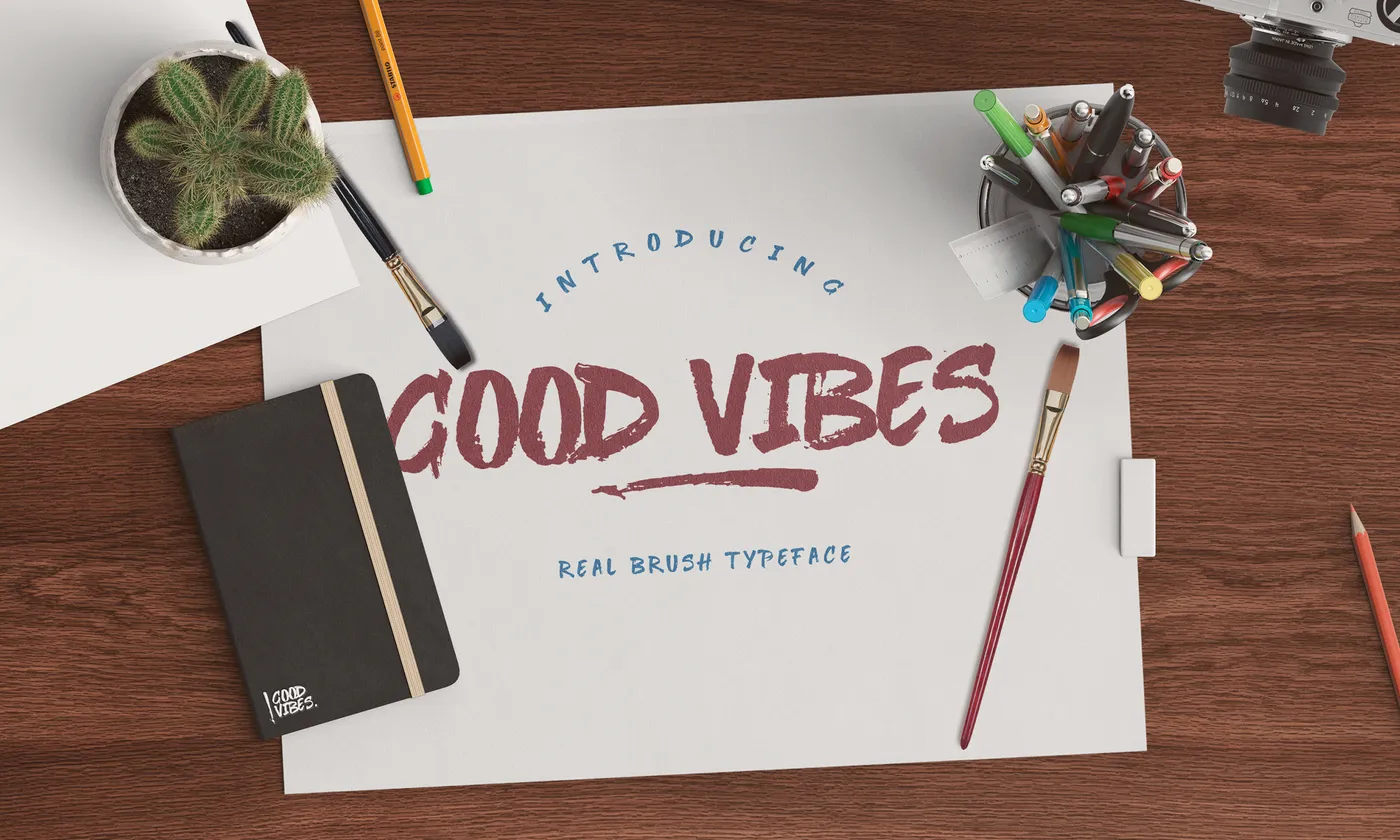
Good Vibes Brush Font – Download Grátis
Descubra a beleza contida na Good Vibes Brush Font, uma fonte script criada com amor pelo designer Hamilton. Esta fonte é perfeita para aqueles que buscam um estilo de brush que se destaca em seus projetos digitais. Ela oferece um toque especial e encantador, especialmente adequado para aplicativos como logos, anúncios, cartões postais e criações gráficas no geral. Good Vibes é mais do que simplesmente uma fonte: ela é um sentimento, uma energia positiva que se transfere de cada traço à outra. Cada letra foi criada a partir da forma como seu designer Hamilton tocou o papel com sua caneta, capturando a finura e a força das suas vibrações brutas para te oferecer uma experiência visual única. Com Good Vibes em seus projetos, você não apenas adquire um recurso gráfico versátil; você também incorpora uma energia positiva que pode animar qualquer design. Essa fonte de brush é perfeitamente adaptável a diversos tipos de trabalho gráfico e pode enriquecer seu processo criativo com um toque especial. Adquira Good Vibes Brush Font hoje, para dar vida à sua próxima ideia visual, transmitindo boas vibrações que irão cativar os olhares dos seus leitores ou consumidores.